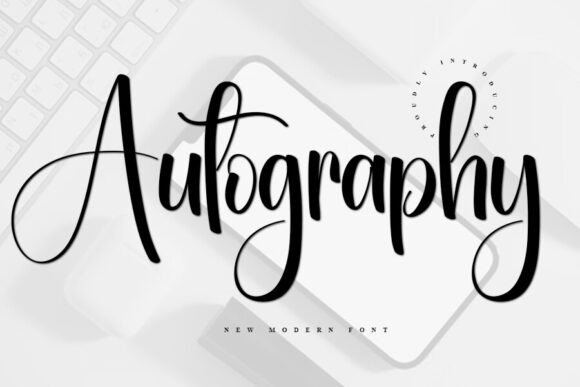
Autography
Якщо ви шукаєте високоякісні ресурси, такі як Autography, цей преміум-пакет є фантастичним вибором для ваших творчих проектів.
Створений з високою точністю, Autography забезпечує чисті вектори, плавну типографіку та комерційну ліцензію для вашого спокою.
Незалежно від того, чи створюєте ви продукти POD (друк на вимогу), весільні запрошення або графіку для соціальних мереж, Autography стане ідеальним вибором.